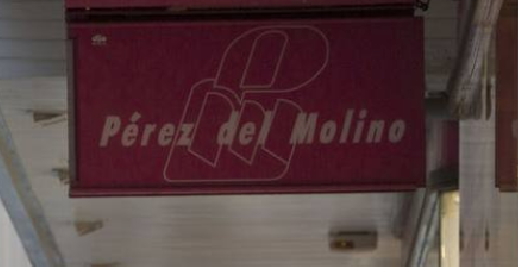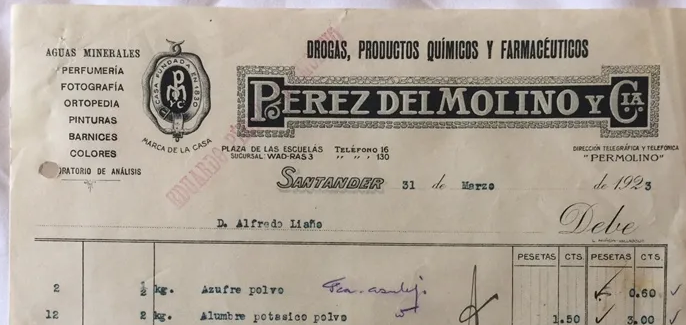
Pérez del Molino
Si hubo en Santander unos almacenes que fueron parte intrínseca de Santander, esos fueron los de Pérez del Molino. Fundados por Eduardo Pérez del Molino y Rosill0 a finales del XIX, este farmacéutico ya poseía en Torrelavega una laboratorio y farmacia. Decir, que Pérez del Molino fue uno de los protagonistas en el descubrimiento de las Cuevas de Altamira en 1857. ¿cómo? muy fácil, Pérez del Molino era amigo de Marcelino Sanz de Sautuola, y además ya exploró el Balneario de Torrelavega, de Hoznayo y la Cueva de las Brujas (Suances). Tras el hallazgo, Sanz de Sautuola se lo dijó a él y Eduardo de la Predaja.(1) Después ambos, junto otro grupo de intelectuales del momento, fueron del grupo que apoyaron a Sanz de Sautuola en la reivindicación de la autenticidad de las pinturas. La figura de Pérez del Molino Rosillo, que fallece en 1933, es de esas que en la ciudad fue importante. Aparte de lo comentado anteriormente, también fue presidente de la Cámara de Comercio de Cantabria en 1914 (3), y Presidente del Depósito Franco del Puerto de Santander en 1923.
El local propiedad de Pérez del Molino estaba en la calle Juan de Herrera, junto a la Anunciación, era un solar que perteneció a los Jesuitas. Pero es en 1947 tras el Incendio de Santander del 41, cuando un gran edificio promovido por Pérez del Molino Herrera, hijo de Rosillo, es levantado por Rasines del Castillo. Desde entonces los Almacenes de Pérez del Molino serían uno de los iconos comerciales de la Ciudad ya que «dentro se incluían los servicios de Farmacia, Ortopedia y Cirugía, Perfumería, Objetos de regalo, Mercería, Papelería, Ultramarinos, Ferretería y Droguería, dotados de todos los servicios auxiliares, tales como Laboratorios, Peluquerías, y Salón de Belleza» (4)
El 29 de febrero de 2016 es la fecha del cierre definitivo a más de 100 años de historia y sus locales son vendidos a franquicias que son sus ocupantes hoy día.
Aunque ha pasado por diversas imágenes gráficas, la aquí recuperada, es la última época desde los 80-90 hasta su cierre. Con ese magenta de fondo y el logo de juego en forma de ideograma de mano con la P y la M.
Fragmento factura de 1923 con el membrete. Fuente: todocoleccion.net
Vista general de los almacenes antes de su cierre. Fuente: Diario Montañés
Logo detalle. Fuente: Diario Montanés.